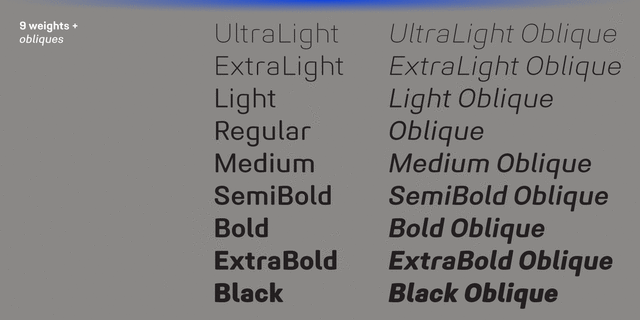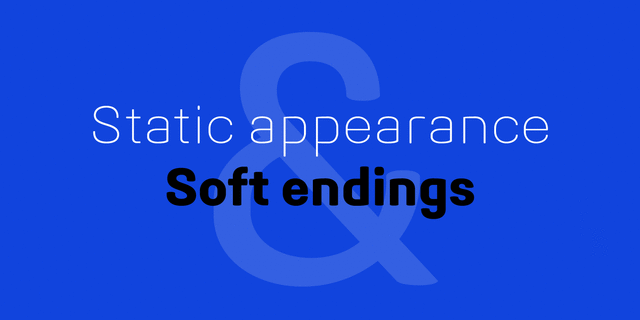
Midpoint Pro – скругленный бесшиповый технологичный гротеск. Чередование открытых и закрытых форм повышает читаемость в небольших кеглях и создает яркую текстуру. Шрифт имеет целый ряд назначений, включая плакаты, корпоративный брендинг, экранный дизайн любого типа, например, веб-сайты или пользовательский интерфейс приложений. В гарнитуру Midpoint Pro входит 9 насыщенностей + наклонные начертания, каждое из которых поддерживает многочисленные языки на латинице, а также большинство кириллических языков. Шрифт имеет многочисленные OpenType-фичи: лигатуры, капитель, 4 набора цифр, 2 стилистических набора, дроби и индексы, адаптивная пунктуация, а также языковые альтернативы. Шрифт разработал и выпустил Олег Лищук в студии Mint Type в 2016 году.
Ассоциации c начертанием Midpoint Pro Black
Качества и характер:
деловой ,
серьезный ,
стабильный ,
статичный ,
устойчивый ,
инженерный ,
точный ,
логичный ,
ровный ,
понятный ,
доступный ,
городской ,
качественный ,
западный ,
спокойный ,
современный ,
техничный ,
уверенный ,
надежный ,
спортивный ,
важный ,
убедительный ,
мужественный ,
мощный ,
сильный ,
авторитетный ,
заметный ,
тяжелый ,
индустриальный ,
техногенный ,
гладкий ,
крутой ,
футуристичный ,
сексуальный ,
мягкий ,
резиновый